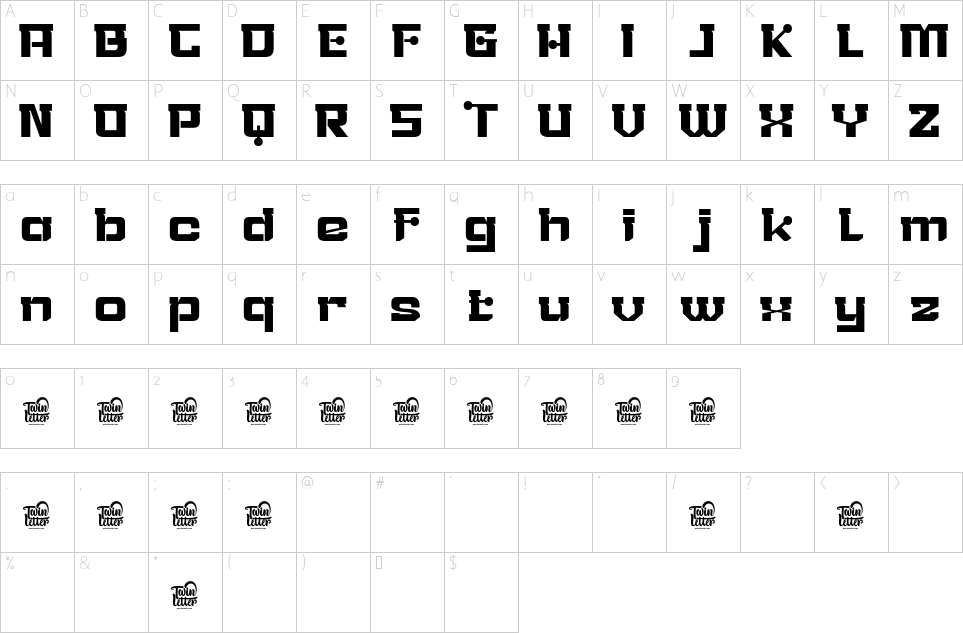
Aqui está uma descrição em português do Brasil para a página de download da fonte ‘Gunec Font – 1001 Free Fonts’: Através deste portal, você pode obter a fonte gratuita ‘Gunec’, desenvolvida pelo designer não informado. Esta fonte é ideal para projetos digitais diversos, desde o design gráfico até a criação de logotipos e mensagens online. Com um visual moderno e elegante, a fonte Gunec é uma escolha perfeita tanto para quem procura algo simples e funcional quanto para aqueles que buscam algo mais sofisticado em seus projetos. Estamos sempre buscando adicionar novas fontes gratuitas para facilitar as criações dos nossos visitantes. A fonte ‘Gunec’ é uma delas, disponível tanto para Windows quanto para Mac, e já foi baixada 1.183 vezes pelos fãs de design. Se você está procurando por uma fonte que se destaca no seu próximo projeto, a font Gunec pode ser um grande favor.